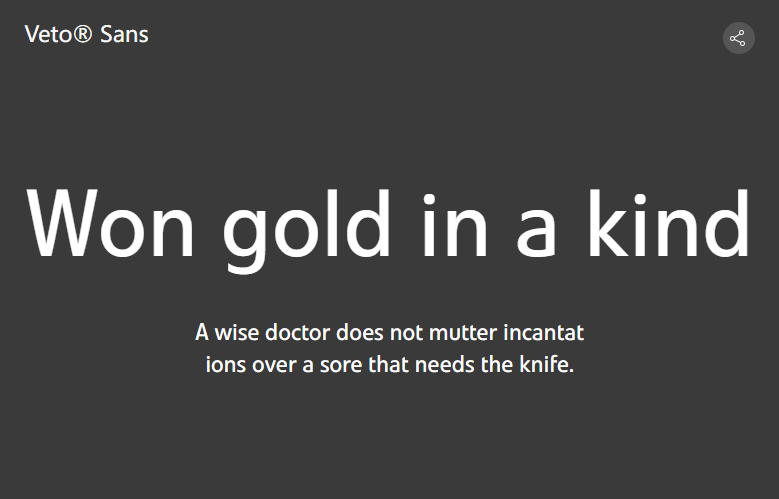
Veto® Sans
Veto® Sans,这款字体结构工整、笔画清晰,兼顾美观与易读性,适用于标题、正文、海报、包装、LOGO 等多种场景。字形优雅稳定,风格百搭耐看,适配日常排版与创意设计,让文字呈现更舒适、更具质感。Veto® Sans一笔一画,皆是细节,以均衡的比例、流畅的线条打造舒适视觉体验,字形端正大气,风格简约现代。无论是商业设计、品牌宣传还是日常排版,都能轻松驾驭,让文字更有格调与力量。Veto® Sans字体下载。
字体品牌: Monotype 设计师:Ganz,Marco 字体分类:无衬线体 字体属性:外文 字符集:Unicode 发布时间: 2019
Veto Sans既高度易读,又非常独特。
Veto Sans在屏幕上和印刷上都具有很好的表现力。精心设计的字重和斜体为这个字体家族赋予了广泛的应用范围,没有一个是多余的。广告、品牌、企业、编辑和互动设计都是Veto Sans的专长,在寻路和其他标识项目中也同样大放异彩。充足的x-height,字母开口,和垂直的笔划结束方式,使Veto Sans不仅节省空间,也很容易阅读。瑞士设计师马尔科·甘茨(Marco Ganz)对早期Veto设计进行了完全的重塑,他致力于保持最纯粹的形式,同时保持轻松自然的风度。Ganz也是一位三维艺术家,他敏锐地意识到字母之间的负空间和字母内部空间与字母本身的正形状同样重要。这种动态平衡,不会给人一种紧迫感,也不会显得匆忙。Ganz还花了很大的精力绘制了一套斜体设计,不仅完美地补充了字重,而且为字族带来了动态的神韵。国际字符集也确保了本地化的便捷性。“Ganz说:“Veto Sans是一种为设计师们寻找新的和不同的解决方案来应对古老的排版挑战的字体。”